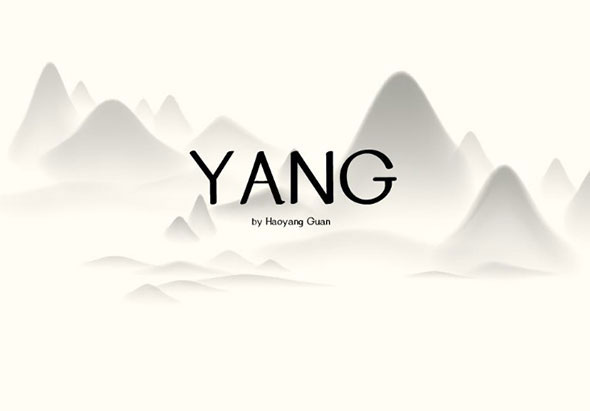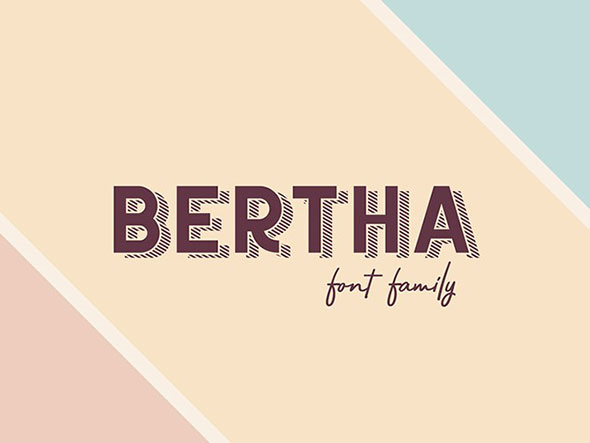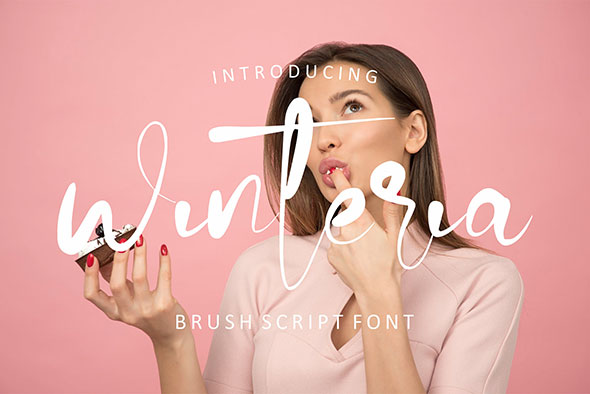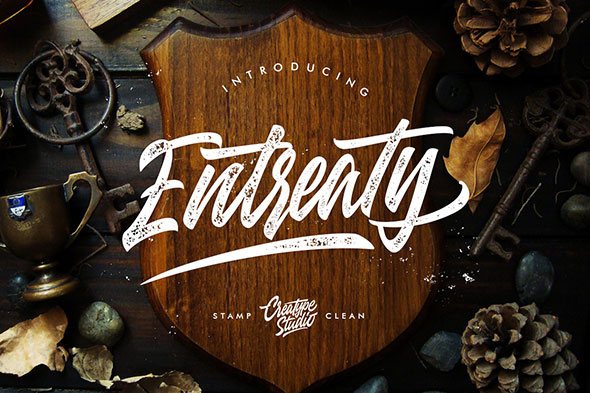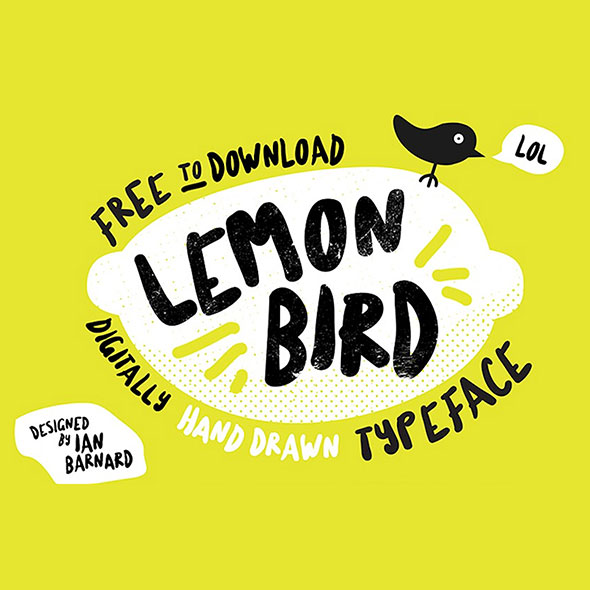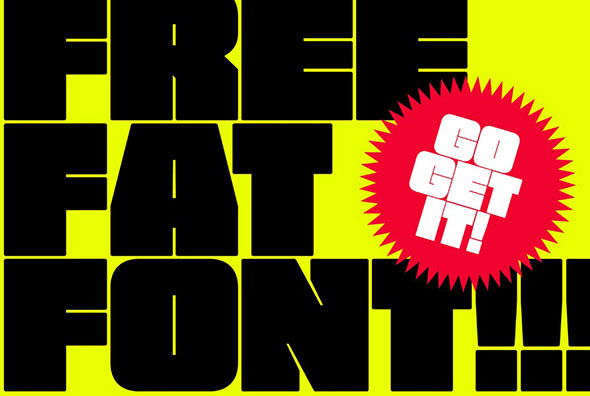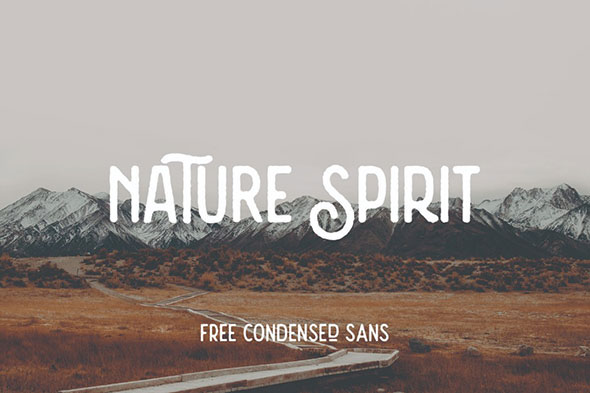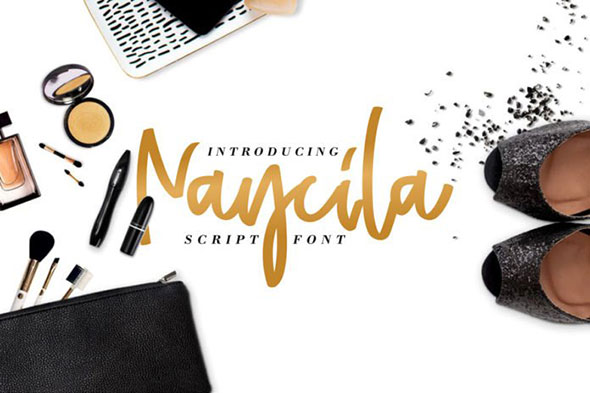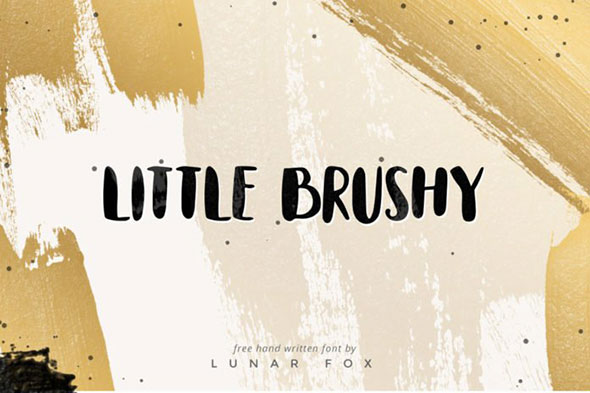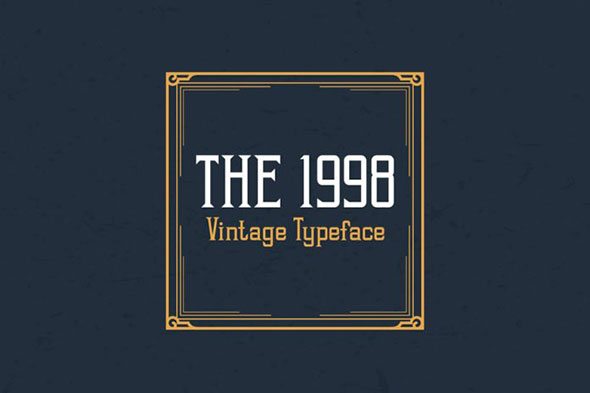
Свежая подборка модных шрифтов
Кому свежие и бесплатные шрифты? На этот раз мы собрали модные начертания. Вы найдете размашистые гарнитуры, написанные кистью, примеры в стиле максимализма, немного винтажных шрифтов, и лаконичные версии. Смотрите, выбирайте и скачивайте, переходя по соответствующим ссылкам!
Yang
Free Fat Font
Emmeline
Nature Spirit
Naycila
Little Brushy
1998 Vintage Display Font
Raitons
Anthares
Made Bruno
Bertha
Winteria
FORMA
ENTREATY
Lemon Bird